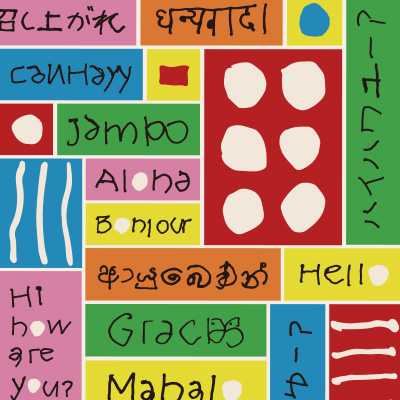
World Greetings
毎日の一言が、世界とつながる。
アロハ〜!ハワイアンズ!すてきです!クッキーの箱にしたいです。みっくすクッキーオススメです。いかがですか?(Kenya Konishi)
本作品はワングラフィックにもパターンにもなるマルチグラフィックです。おかし屋ぱれっとの工房で見た小西さんの「Aloha〜!」という挨拶からコミュニケーションが広がるように、この作品は言葉のブロックを自由に組み合わせてどこまでも広げることができます。アルファベットの“O” や “L” を図形に見立ててアイコニックなポイントを作ったり、遊び心もいっぱいな作品になっています。(Yuka NAMIKI)
作者の小西さんは、おかし屋ぱれっとに出勤すると「Aloha~!」とあいさつします。なぜか「アップル~!」の時や「セブン~!」の時もあります。みんなの中に小西さんが流行らせた言葉や代表的な世界のあいさつに加え、おかし屋ぱれっとがこれまで国際交流をしてきた国々のあいさつ(スリランカ・マレーシア・ネパール・モンゴル)も描きました。様々な人と出会って可能性を広げていきたい!というぱれっと一同の気持ちが表れたパターンです。(工房ぱれっと)